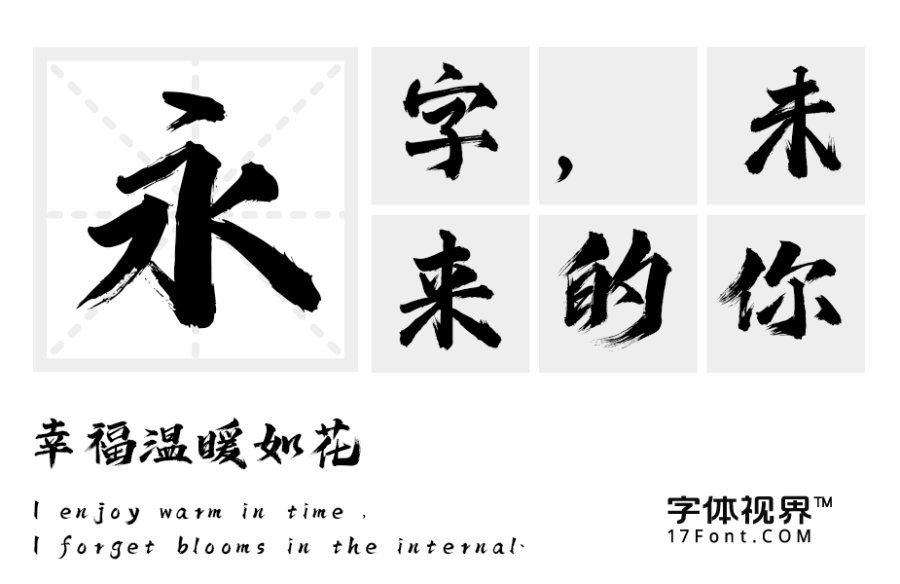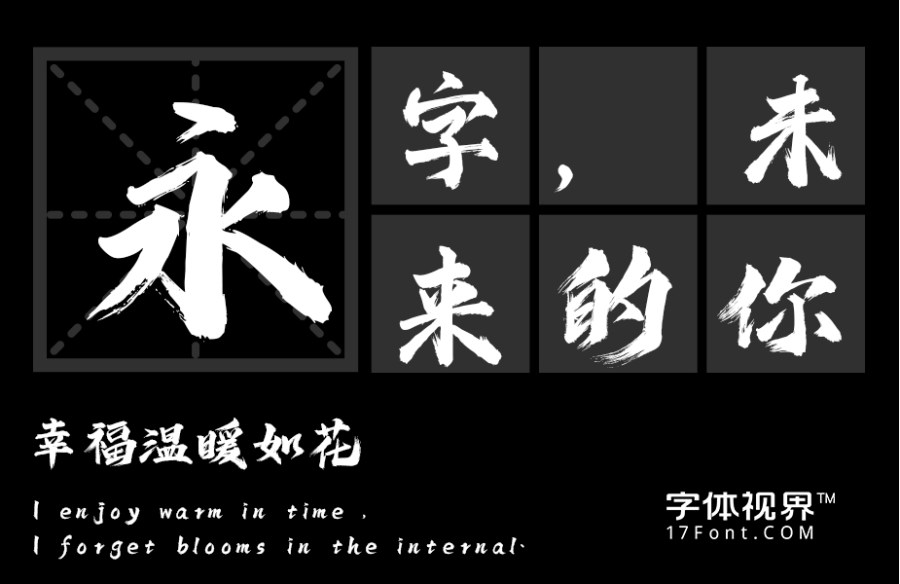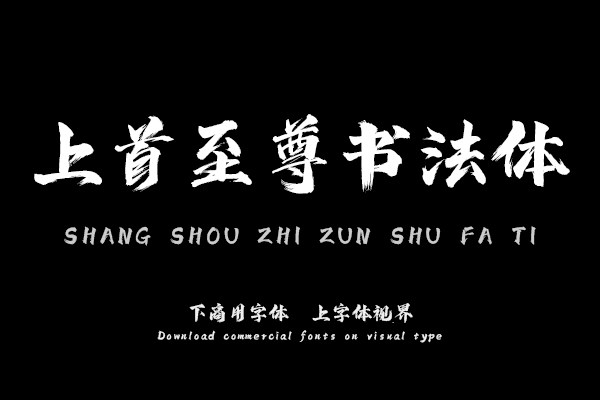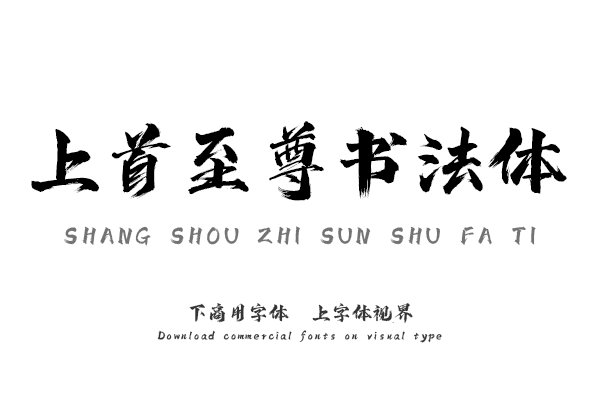
上首至尊书法体,字体笔画狂野,笔画特点夸张,字体圆润又不失刚劲,具有书法特点和创意性,适用于搭配标志、广告标语、商业广告等高端属性。购买须知:“下载服务费”与“字体VIP”所获得字体 仅用于个人非商用, 商用请联系付费授权。本字体为电脑用字,手机没有root权限不支持直接手机换字(手机如何root,请自行百度搜索教程)。购买前请先 了解清楚后再付款 ,字体为虚拟产品无法回收 一旦购买不支持退款。